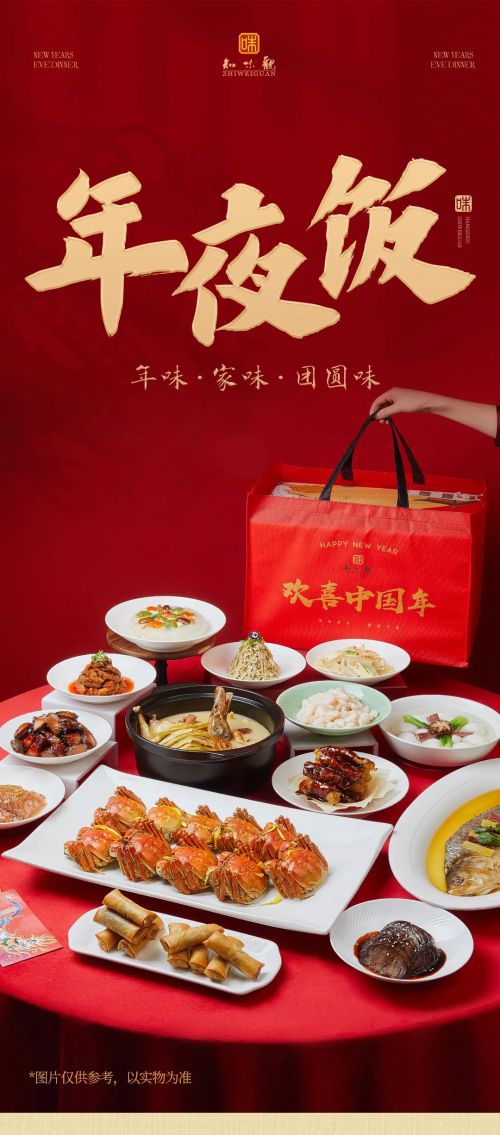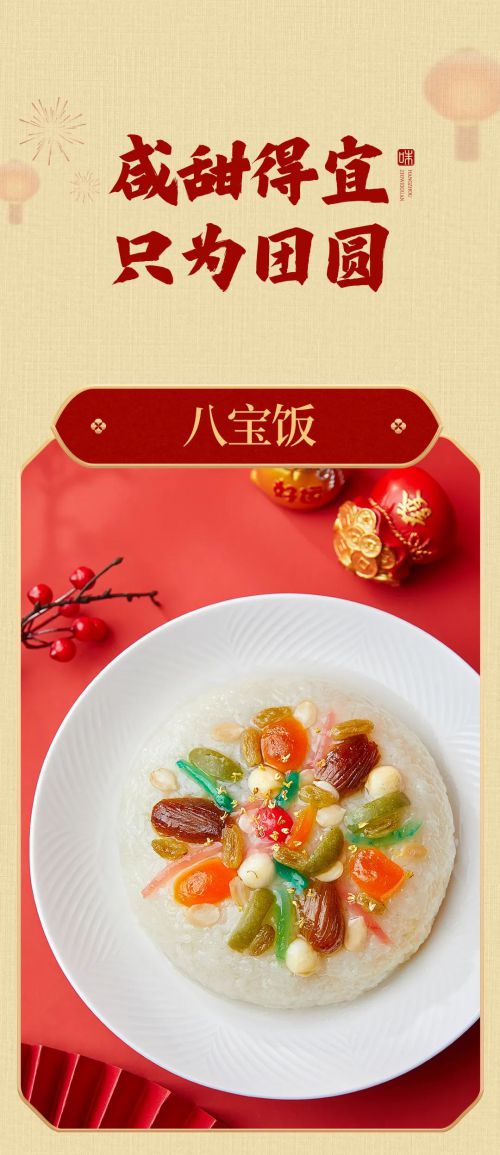
点字龙飞手书
点字龙飞手书造型灵感来源于唐朝楷书作品,继承森严法度的结构特点,整齐均匀,放大其丰腴敦厚的造型,辅以灵动巧妙的笔触,飞白自然,独具一格。点字龙飞手书整体浑然天成,方圆之间,气象万千。希望借此字体,表达对独步千古、风华犹存的唐楷的崇高敬意,更希望借此字体,传达一种方正沉稳,圆润豁达的民族品格。